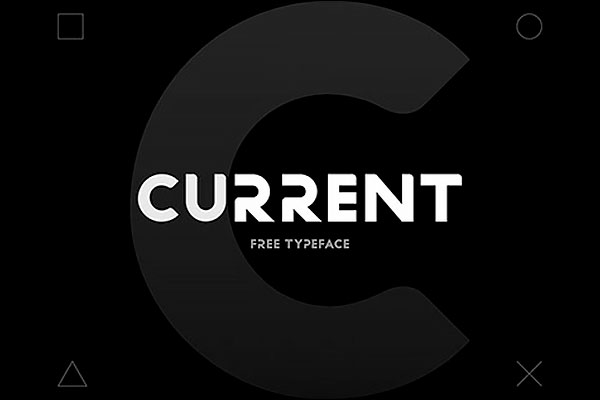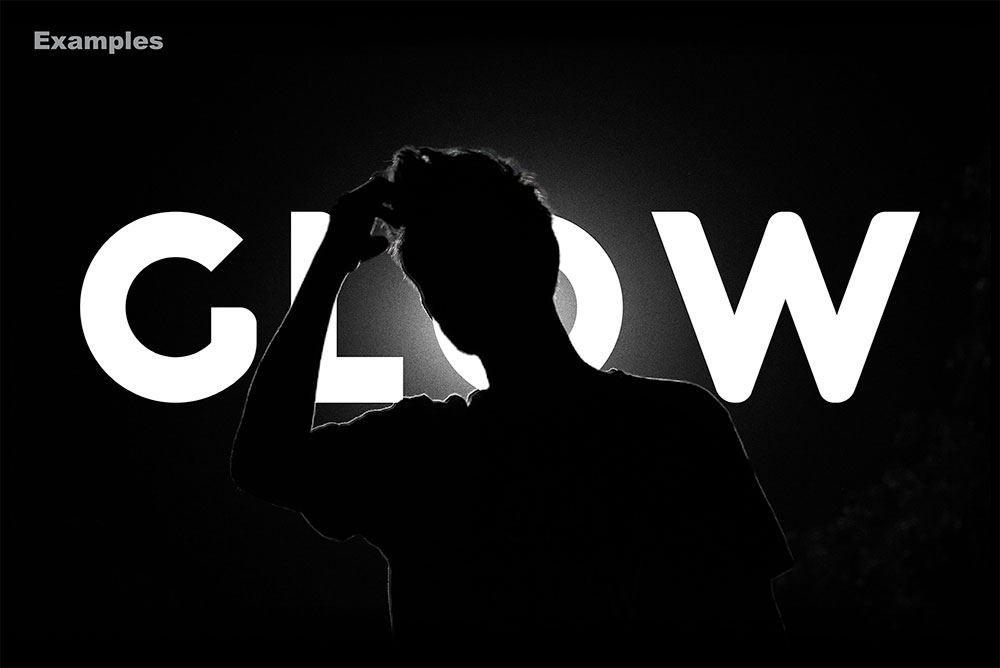
CURRENT字体
CURRENT字体:大胆无衬线,美丽又实用
CURRENT是由Matt Pendrill设计并开发的一款大字体,以其大胆、美丽、无衬线的风格令人瞩目。这款字体凭借其简洁的线条、圆润的特点以及醒目的外观,展现出与众不同的力量与美感。它非常适合用于广告牌、海报以及网站等标题,能够为设计作品增添一抹独特的视觉魅力。
CURRENT效果预览